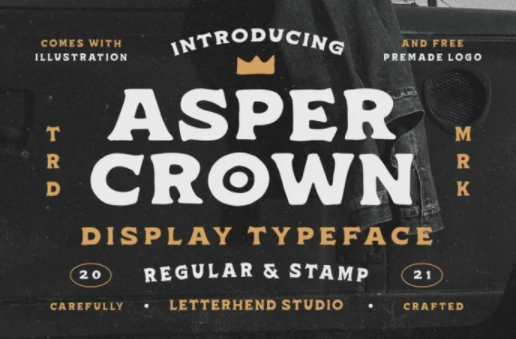
[Fontbundles] Asper Crown Font (2021)
Fontbundles Asper Crown Font (2021)
Asper Crown - сильный и смелый шрифт sans serif с оттенком винтажного вида и ощущения. Поставляется с 38 бонусными иллюстрациями в векторе и бесплатными 12 готовыми логотипами. Этот шрифт идеально подходит для использования в логотипах, заголовках, вывесках и других различных формах, таких как приглашения, этикетки, логотипы, журналы, книги, поздравительные / свадебные открытки, упаковка, мода, макияж, канцелярские принадлежности, романы, этикетки или любой вид рекламы.